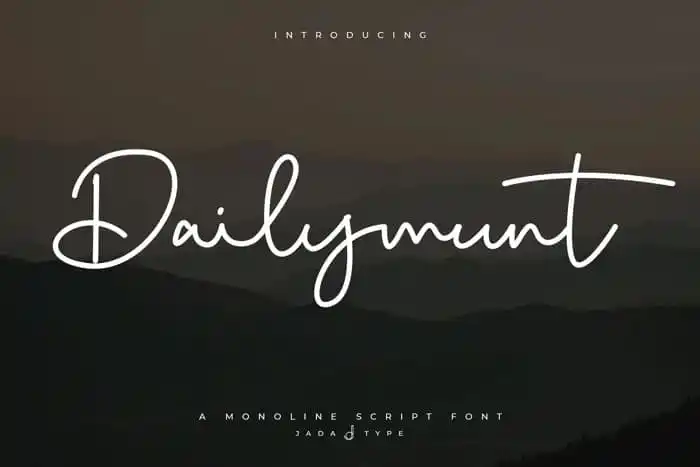
Dailymunt Handwritten Font
A Dailymunt Handwritten Font é uma fonte elegante de letra cursiva baseada na expressão do próprio traçado humano. Esta tipografia atinge a beleza e a sensibilidade que surgem nas mãos reais, oferecendo um toque personalizado ideal para criações digitais que precisam de alma humana. Oferecida pelo jadatype, esta fonte é perfeita para adicionar uma pitada única aos posters com citações, cartões de agradecimento, logotipos e até mesmo cartões de visita. Ela dá um toque especial às criações digitais que precisam soar autênticas e criativas, tornando-a uma escolha ótima para designers em busca de um charme especial. Seja na sua próxima arte digital, a Dailymunt Handwritten Font oferecerá um toque único que fará suas criações se destacarem do resto da multidão.